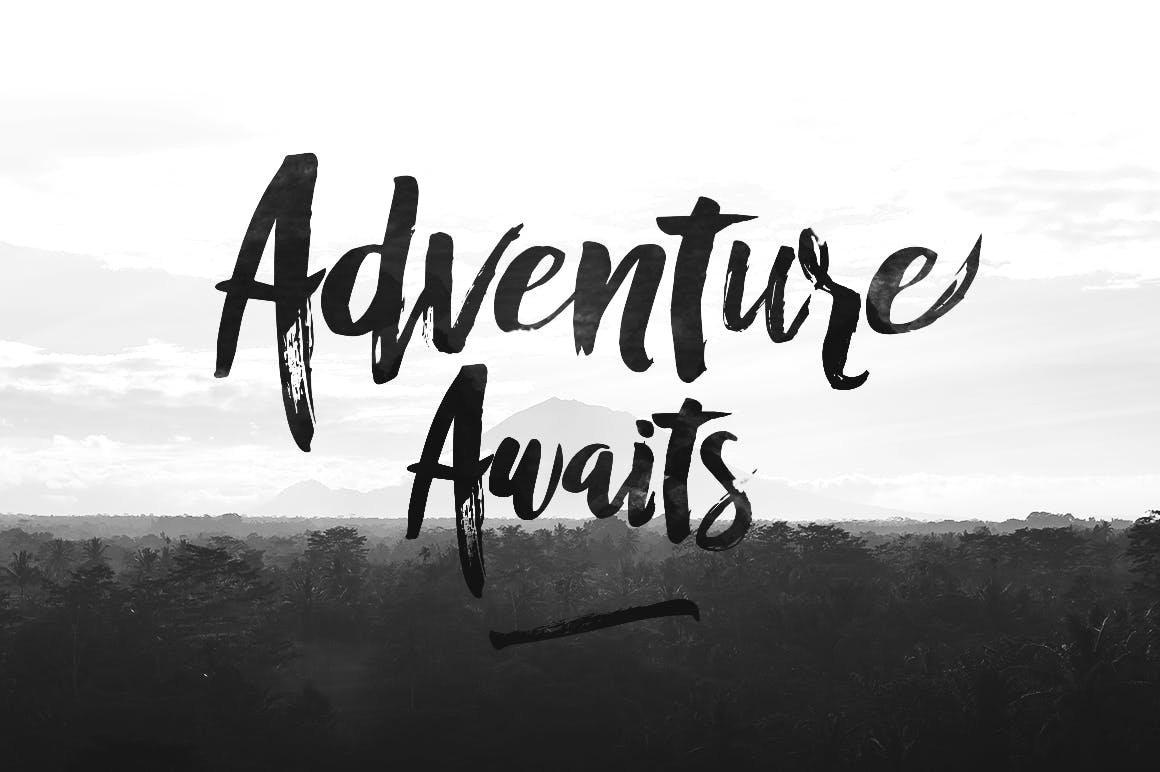
دانلود فونت RofiTaste با طراحی خاص و خلاقانه
RofiTaste Typeface
فونت RofiTaste با طراحی منحصر به فرد، مناسب برای پروژه‌های خلاقانه شما.
معرفی فونت RofiTaste Hand brushed، این فونت با استفاده منحصر به فرد از قلم خشک طراحی شده است که شخصیت خاصی از نوع قلم گرانج را ایجاد می‌کند. فونت RofiTaste برای تولید متن‌های نقل قول، لوگوتایپ، سرصفحه‌های مجله، طراحی تیشرت و مفاهیم طراحی دستی بسیار مناسب است.